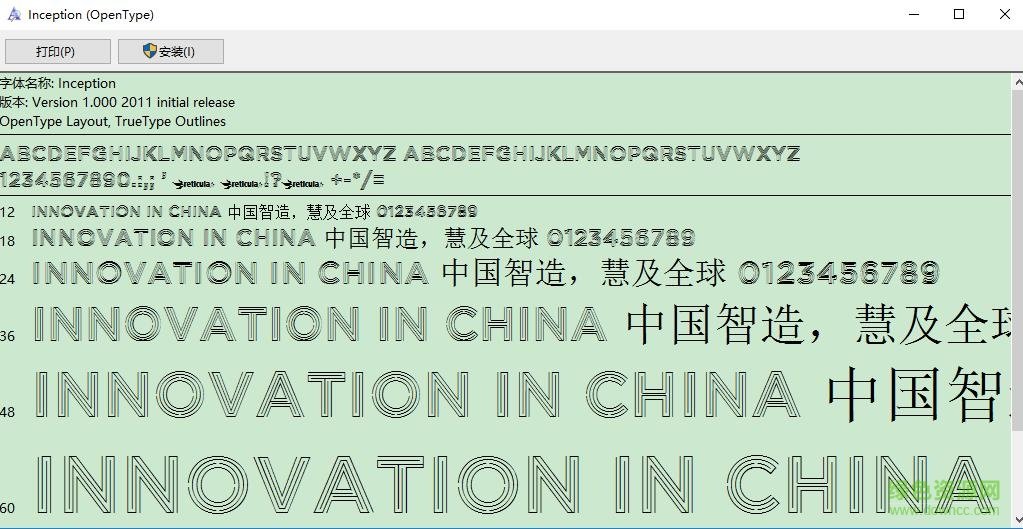
inception是一款非常有特色的英文藝術(shù)字體,這款字體字形簡(jiǎn)約,簡(jiǎn)潔爽朗,整體效果非常出色,喜歡這款字體的朋友歡迎來綠色資源網(wǎng)免費(fèi)下載使用!
inception字體整體效果非常的出色,字形鮮明亮麗,可以廣泛應(yīng)用于美術(shù)設(shè)計(jì)、廣告設(shè)計(jì)、宣傳海報(bào)、ppt、影視制作等領(lǐng)域!